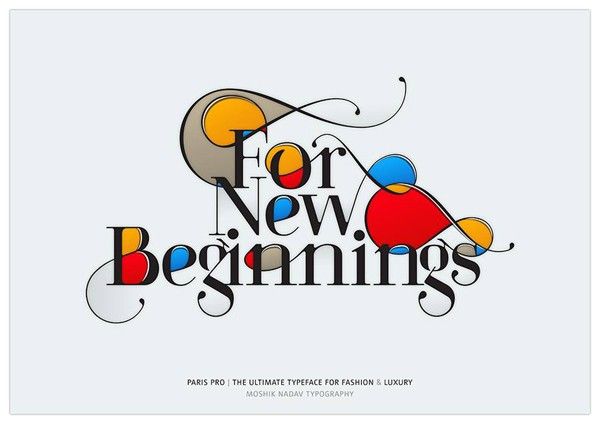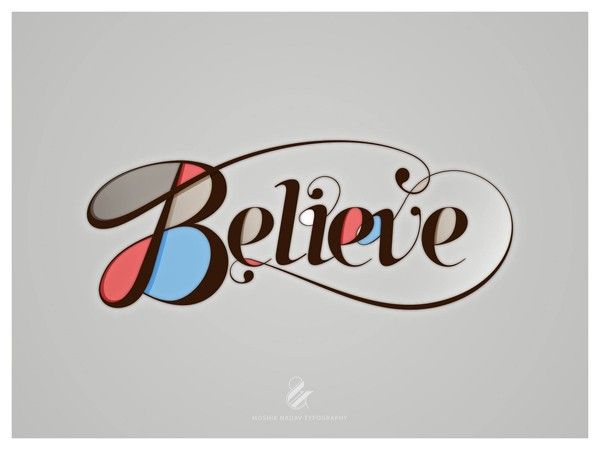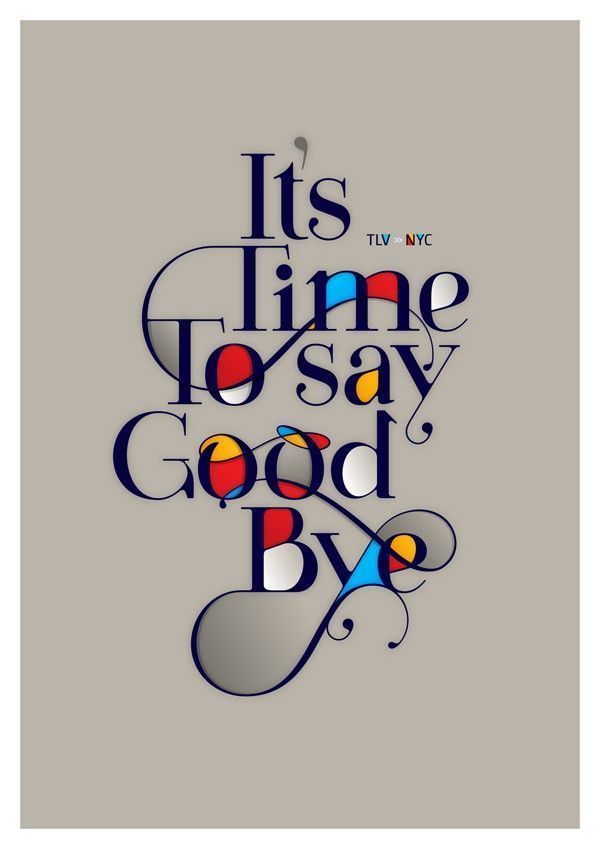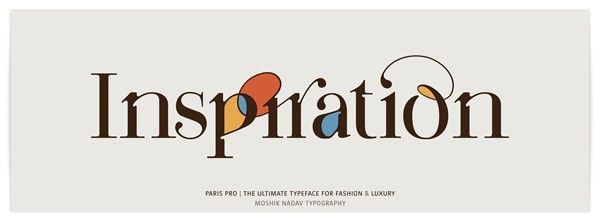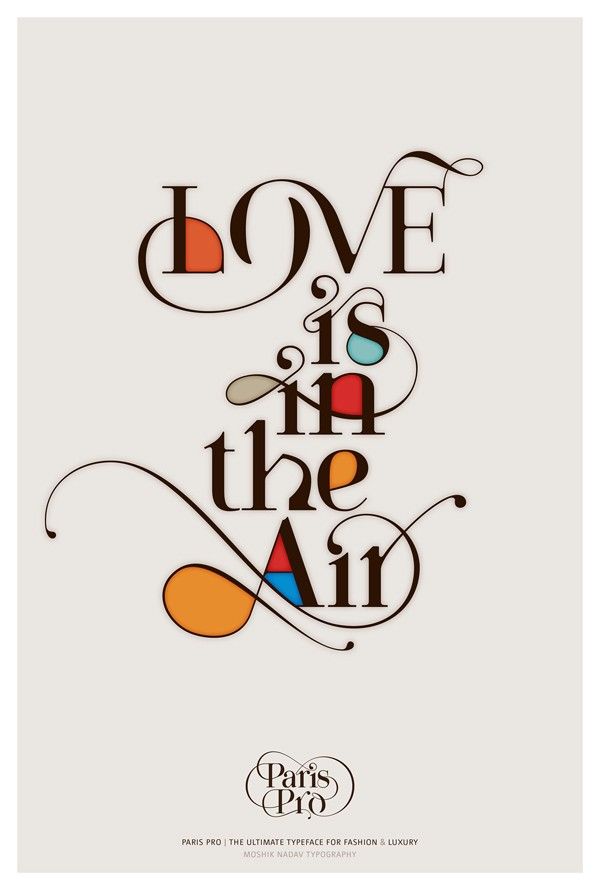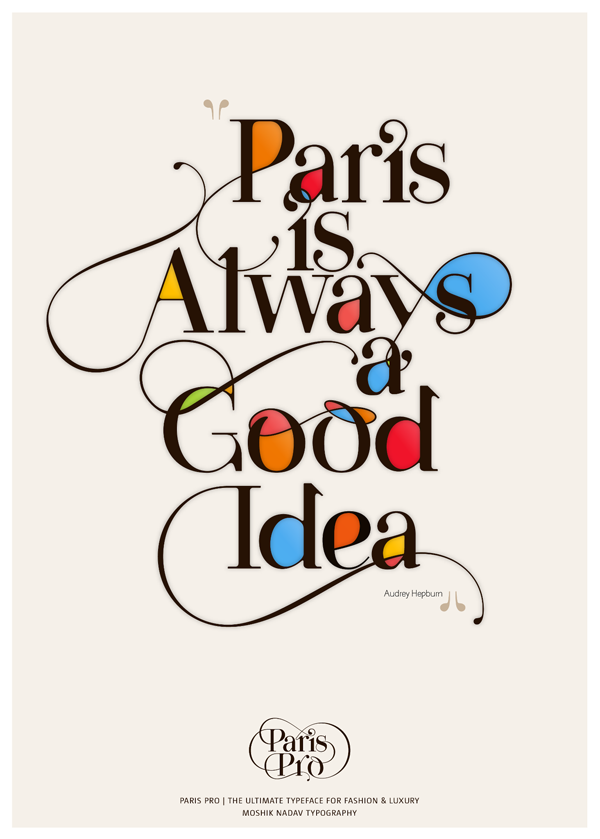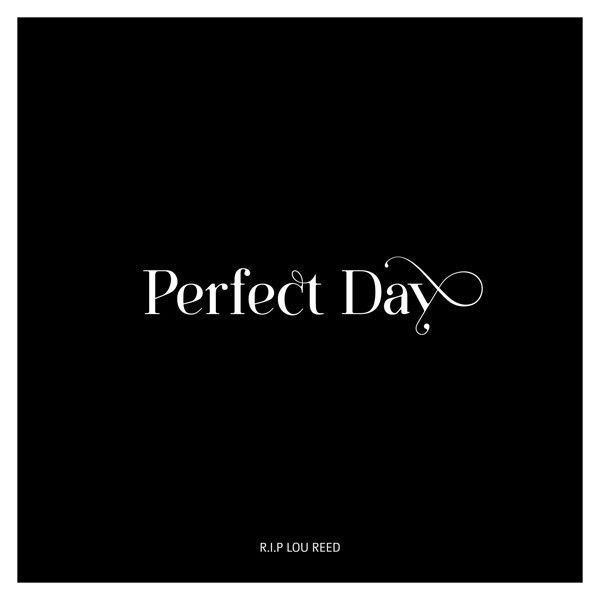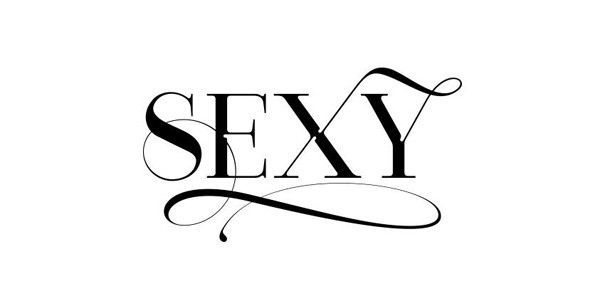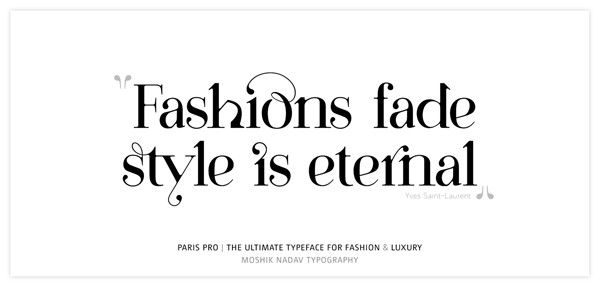
Moshik Nadav et l’impression devient art
Moshik Nadav l’imprimeur master qui va te subjuguer avec ses lettres
Il est vrai que je t’avais déjà parlé de street-art mais aussi de calligraphie, qui est l’art de bien former les lettres, en faisant danser la plume entre tes doigts; cependant, je ne t’ai pas encore susurré toute la beauté de la typographie. La typographie désigne les différents procédés de composition et d’impression utilisant des caractères et des formes en relief. Tu l’auras compris, la typo connait son essor le plus remarquable avec l’arrivée de l’imprimerie bien que sa pratique existe depuis bien avant.
Pour être sûr que tout le monde me suit, la typo, c’est l’art d’assembler des caractères mobiles  afin de créer des mots et des phrases en vue de les imprimer, Gutenberg si tu nous regardes (il n’est que l’inventeur de la technique conjointe au niveau de l’impression à caractère mobile, pas de l’imprimerie), sois fier de nous. La typo a été pratiquement la seule forme d’impression jusqu’au 20 ème siècle, mais c’est aussi la manière de se servir des caractères : choix de la police, choix de la font et de la mise en page. Bon toute cette litanie à propos d’impression pour en venir à cet artiste du nom de Moshik Nadav.
Moshik était employé dans une grande agence de pub à Tel Aviv, lorsqu’il décide de se consacrer à sa grande passion, la typographie, et ouvre ainsi sa firme spécialisée dans la mode et le luxe à New York. Son entreprise dans cet art connaît de nombreux adeptes avec ses 100000 fans sur Facebook, preuve qu’il y a encore des amoureux des belles lettres. Enjoy !